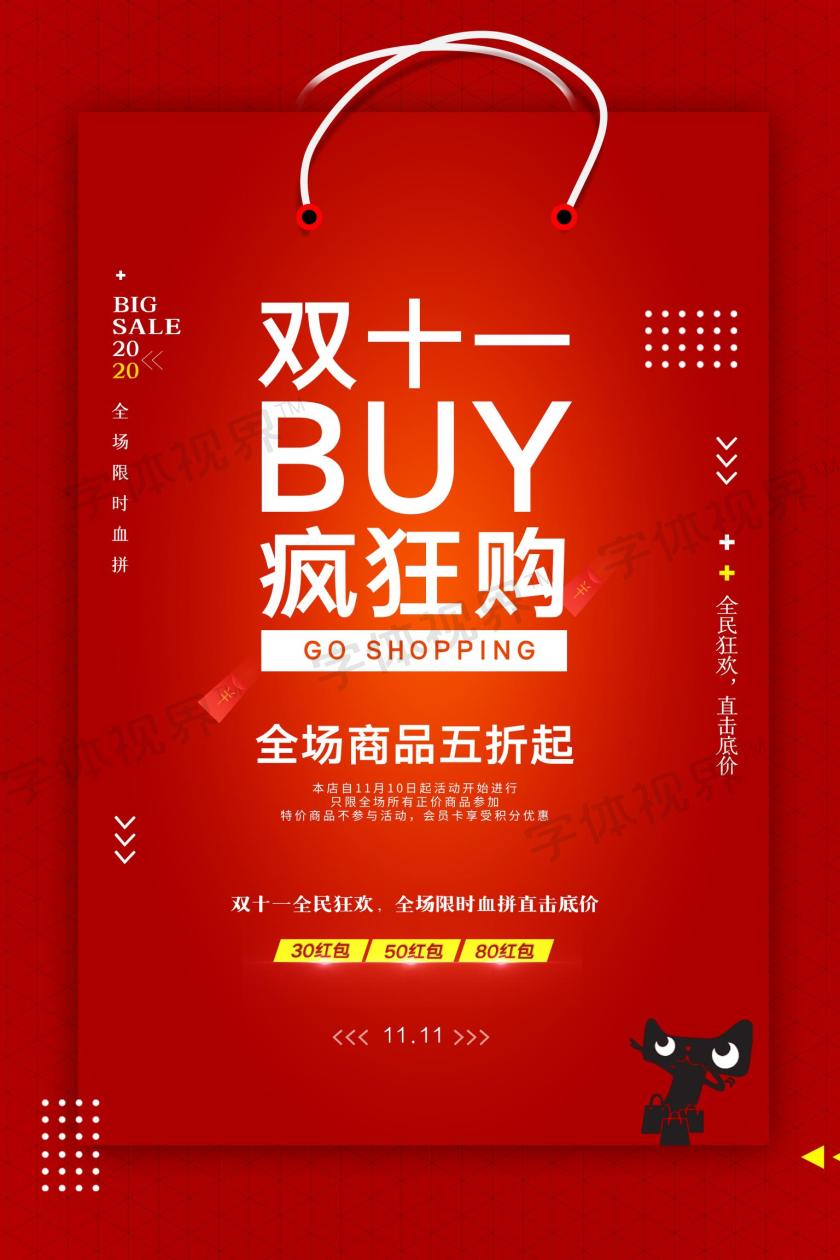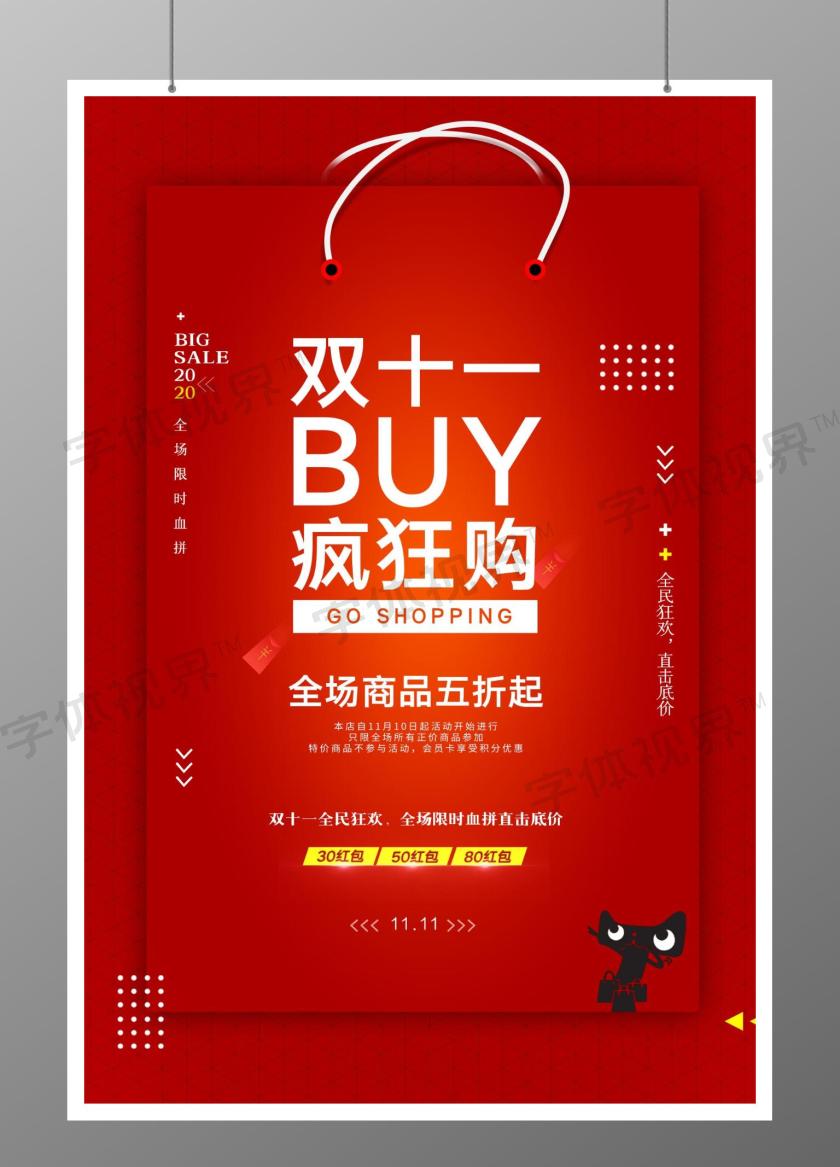
双十一狂欢购活动促销宣传海报
这是一张关于双十一活动促销海报设计图片,喜庆风格设计,以红色为主色调,设计成双十一活动促销海报模板,主体文字图片皆可替换修改,也可用于双十一活动促销海报、双十一狂欢海报、双十海报、狂欢海报、十一海报、狂欢购海报、活动宣传海报、促销活动海报、促销宣传海报、促销双十一海报、宣传活动海报、宣传促销海报、双11活动海报、双11促销海报、双11宣传海报、双十一活动海报模板素材,格式为PSD,作品编号:517158,尺寸为3543*5315像素,欢迎会员免费下载。